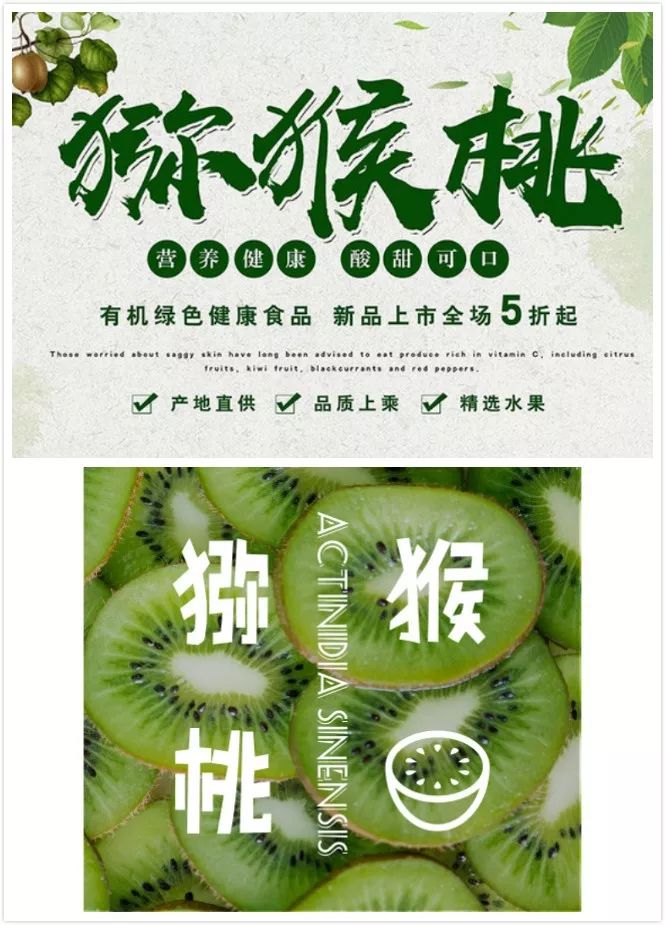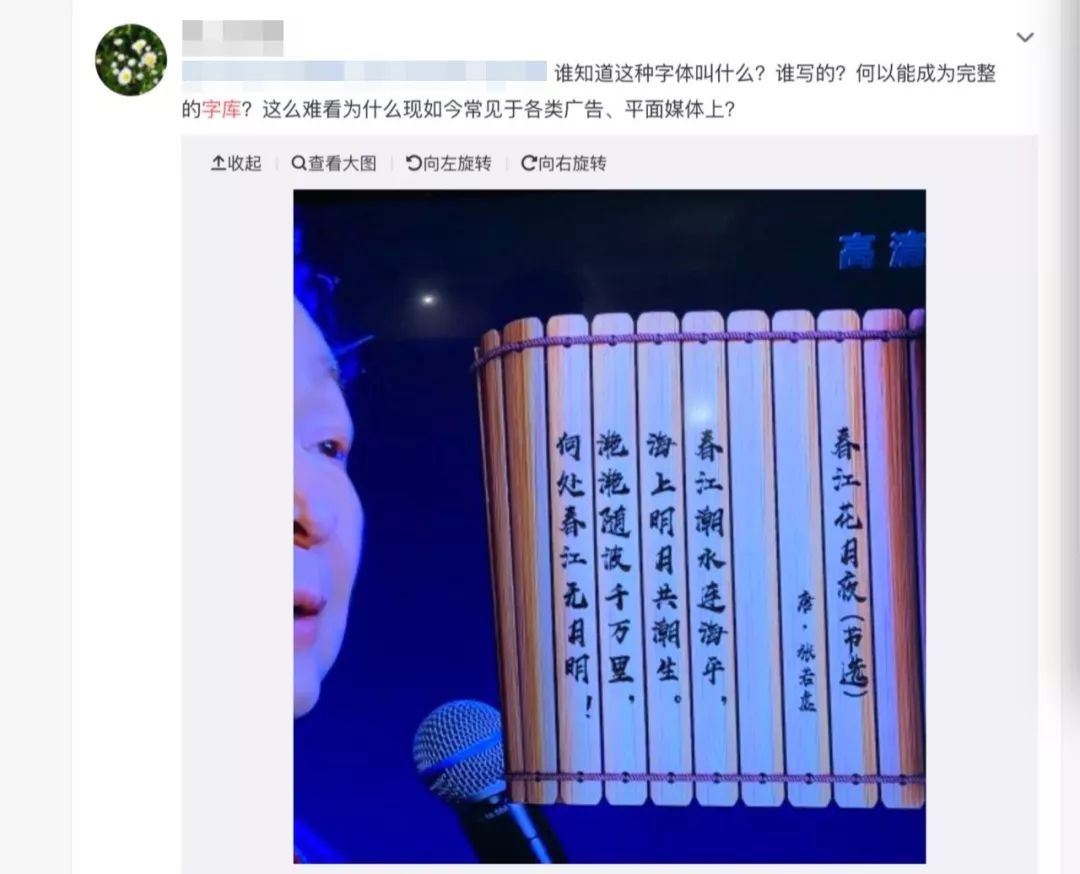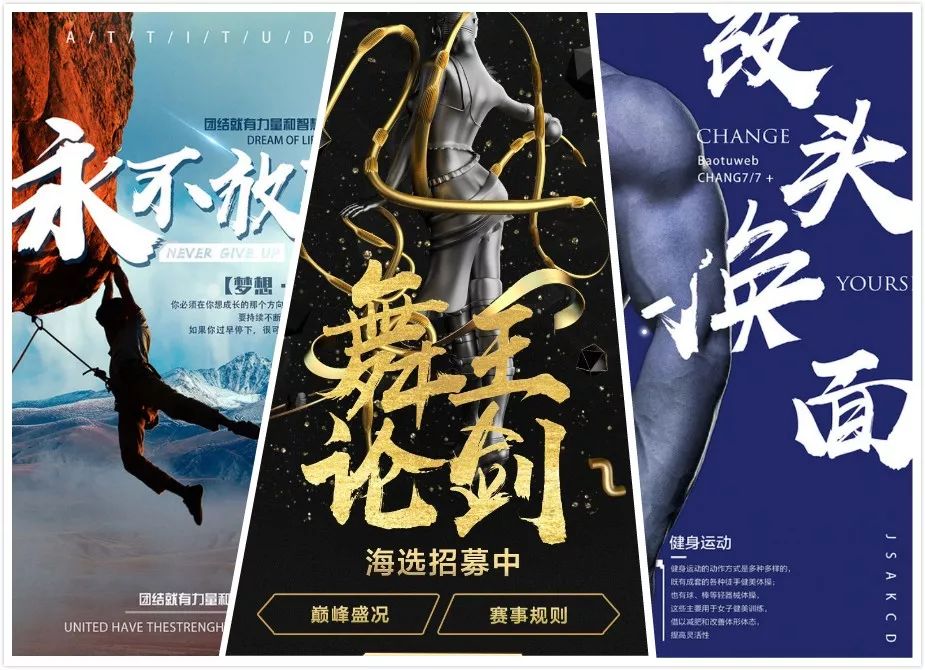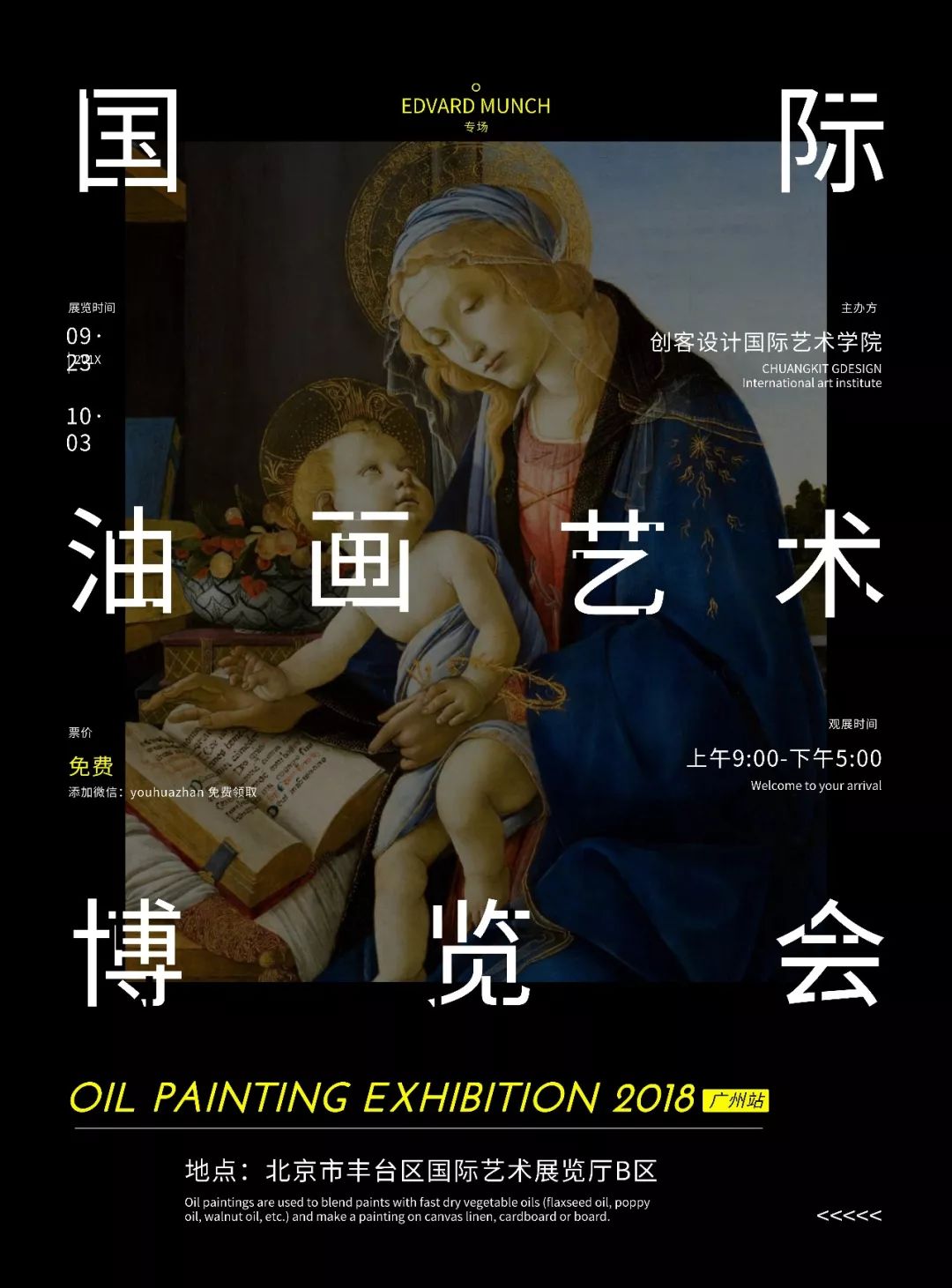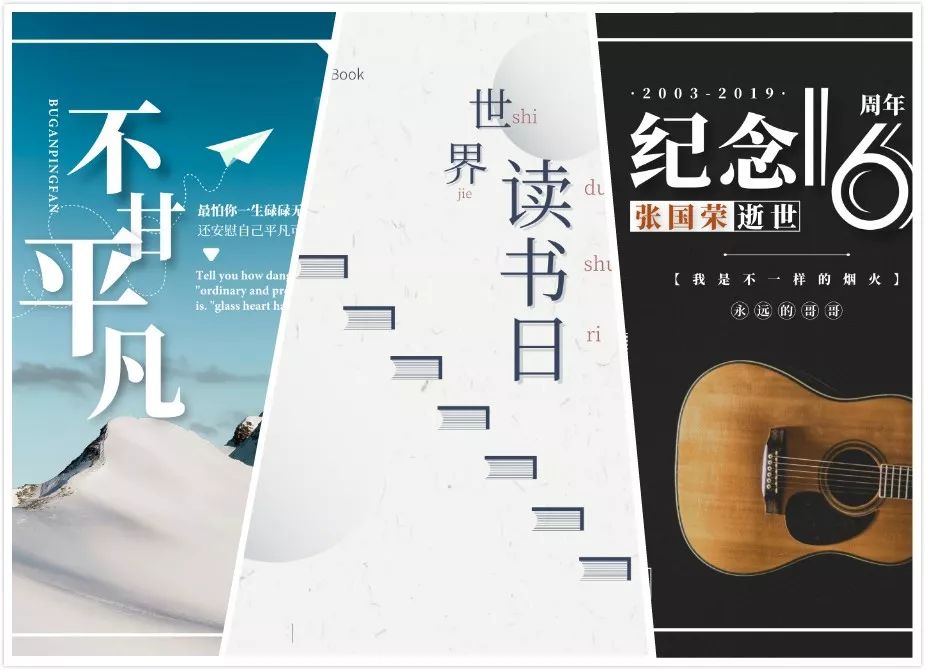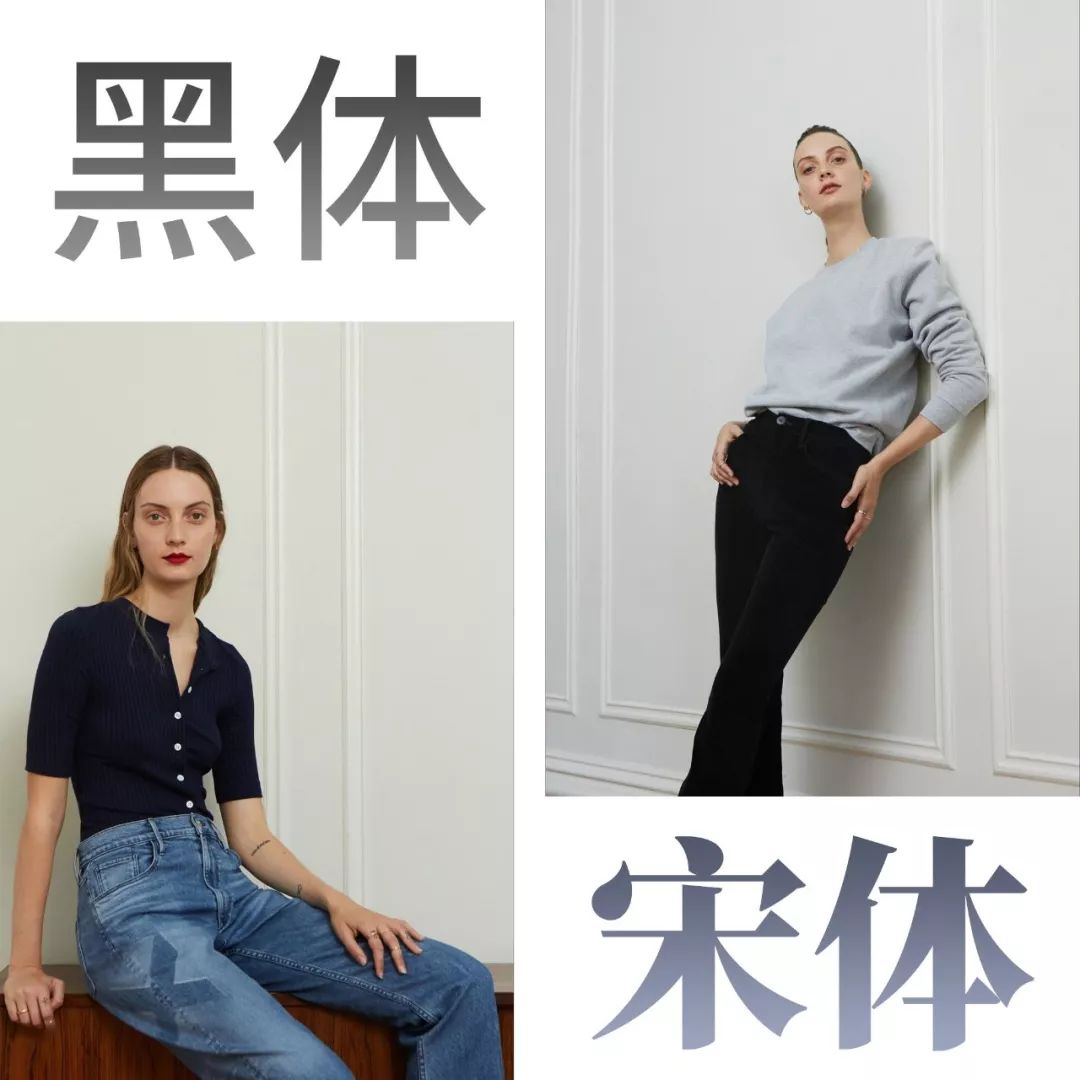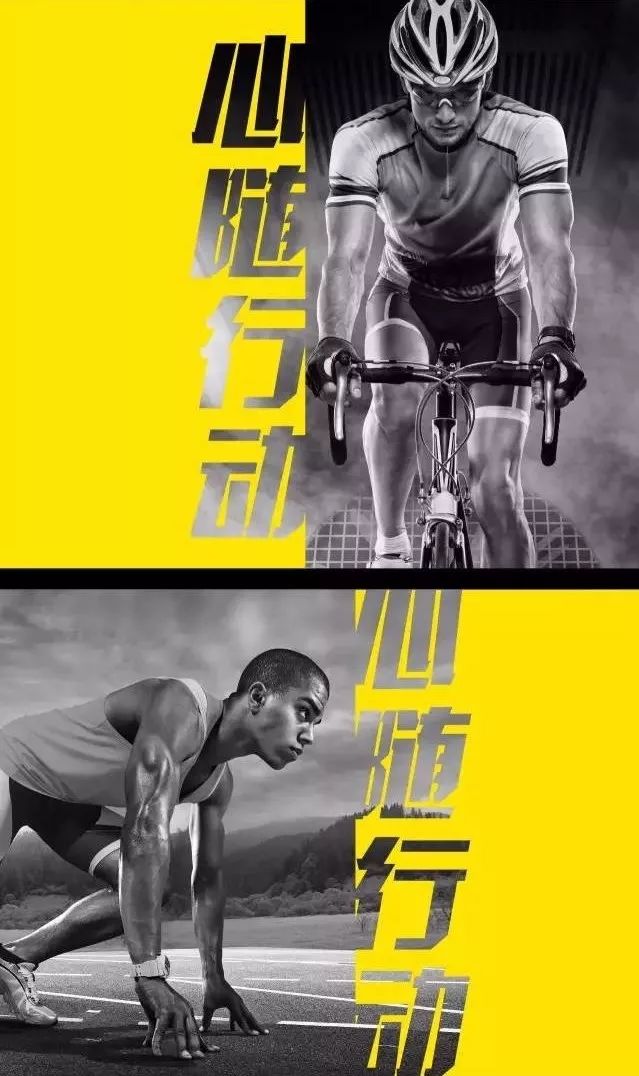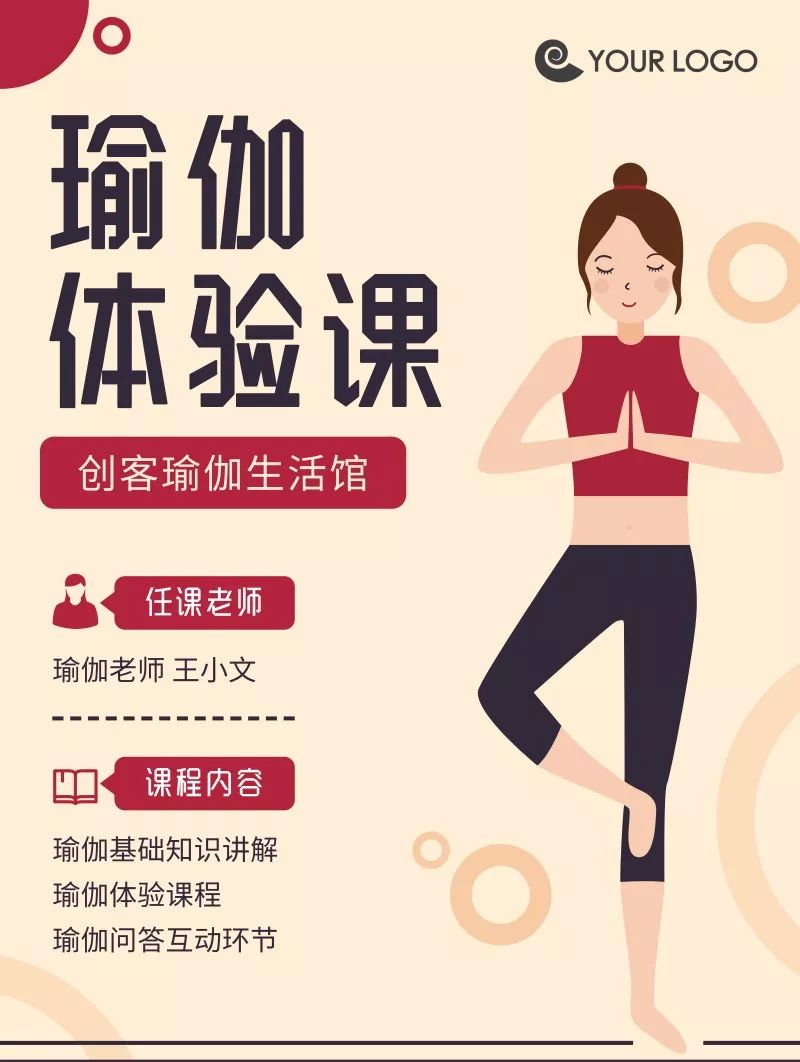
搞定了字体版权,再来帮你如何选择字体?
不过这都不是今天柚子想说的。我想探讨的是,你搞定了版权以后,怎么用?这个话题说大不大,说小也不小,但它确实是现实存在的问题。
滥用爆款字体
举个最简单的例子,当小红书、抖音上的网红博主,给你推荐这推荐那,是不是有一种不拿下就跟不上时代的感觉,满眼都是爆款,满脑都是买它~
字体也是如此,买版权的人,可能不是设计师,只是单纯地根据推荐来下单,“今天有哪些好看的字体“,”明天有哪天热门的字体”……
花最少的时间,拿下市场验证过的东东,这无可厚非,但接下来的高矮胖瘦、男女老少、性格色彩、应用场景,就考验设计师的功力了。
比如汉仪尚巍手书,你可能经常看到它霸气侧漏的样子!
但红得发紫的后遗症,你可能没想到,看看这格格不入的食品、动漫。
还有这引起民愤的《春江花月夜》,明明字由上有那么多古典字体,非选这一款,这就好比要金钟国扮贾宝玉,你看得下去啊?
救救尚巍吧!来看一组对比图,同样是猕猴桃,请问哪个你更想买?上面的……感觉齐天大圣会随时出来炸毛,下面的汉仪黑荔枝体,嗯,很想咬一口~
还有这个,你是想感恩呢,还是想让老师感恩呢?看看下面的汉仪铸字美心体,这才得体且温情~
服装搭配的灵感
之所以举尚巍的例子,是因为它应用特别广,出错的几率也大,不代表别的字体就用得对,有时间你可以去官网的案例,火眼金睛一下。
究竟怎么选字体,其实之前在别再晒截图表达情绪了,这才是最高明的输出方式,说过一些,今天我想换个角度,比如你最熟悉的服装搭配。
想象一下,现在已经购入了一批服装(版权),先不论它好看与否,是不是你想要的,但你只能在这里面选,你会怎么配?是不是得先基本款~
别以为思源黑体只能做副标题、正文,加法做得好,也可以C位出道。
减法做得好,也可以很有内涵~
至于思源宋体,天生就带主角光环,只要注重排版,就可以很有诗和远方~
基本款怎么搭都不会出错,既可以内搭(正文),也可以外穿(标题),想要special一点,就看你怎么加减乘除。
不同场景选字体
当然了,基本款肯定不能满足所有需求,不然服装公司该倒闭了,字库公司也没有存在的必要。正因为我们有多重身份,需要穿梭于不同的场合,也要满足不同甲方爸爸的要求,所以才要穿对衣服,选对字体。
这里我又要夸一下口红一哥了,他爆红绝不仅仅是因为他那魔性的OMG,还有他那正中命门的洗脑词,什么“全智贤本人诶”,“初恋的感觉”,“涂上它你就是贵妇”……注意啦,这可不是形容词,而是一种美好的向往,谁听了都会心动,因为那是更好的自己。
不过并不是谁都能说得那么准确,所以也不是谁都能成为李佳琦,这个需要不断练习。下面我们来做个小作业,假如甲方爸爸要你设计一款海报,只说了三个字——运动感,你能发散想到哪些?
▲汉仪程行简
▲汉仪铸字超然体
上面两款都是惯性思维,但不太激烈的运动,想到过吗?
▲汉仪晓波折纸体
除了日常的基本,出行的运动,还有一款被人经常挂在嘴边的,就是“高级”,我百度搜了一下,是这样的~
这还不简单,所有你觉得低级的元素,比如色彩、装饰,统统都去掉,就是高级。
所以显高级感的字体,一定不是花哨的,而是经久耐看的,我选了几个关键词。
▲汉仪雅酷黑
▲汉仪意宋
一个粗,一个细,但共同点都是笔画很微妙,整体不轻浮,看起来很贵~
总结一下,今天从服装搭配的角度,说了一下日常、运动、高级怎么选字体。另外就是一定要多练习关键词,准确、细化地描述你想要应用的场景,那样跟甲方爸爸也可以少点折磨的。先从不出错入手,再解决画面太平的问题,这是我给你的建议,妈呀,都不认识我自己了~